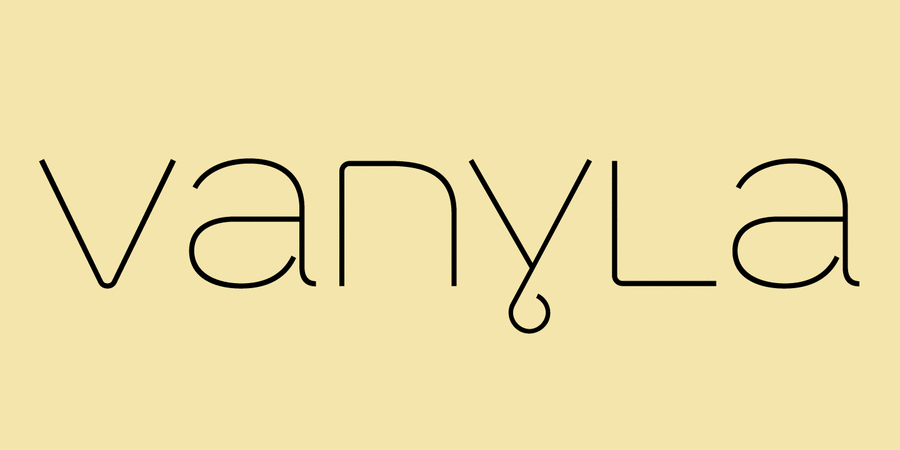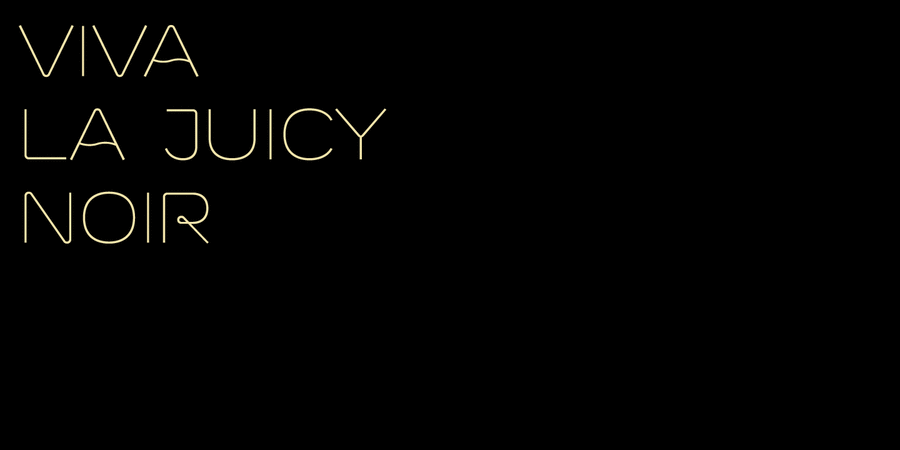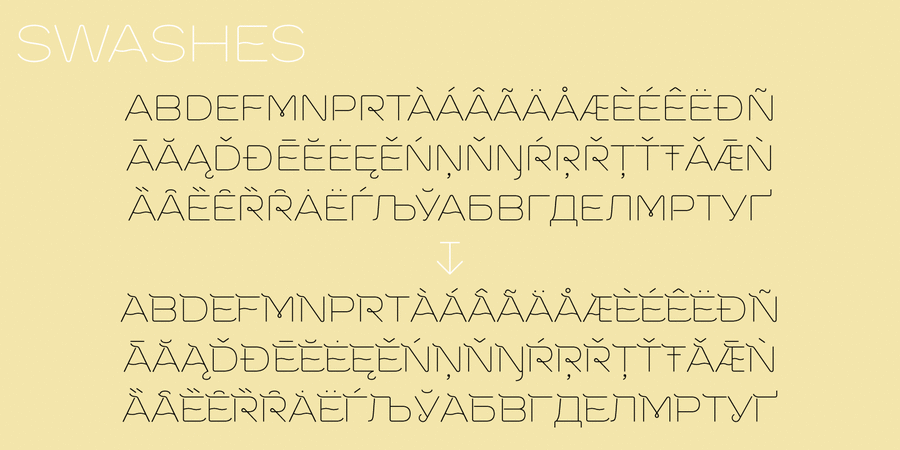
About Vanyla 4F UnicaseШрифт Vanyla 4F Unicase содержит 2 начертания и отлично подходит для рекламы, неоновых вывесок, журнальных заголовков и другой акциденции. Разработан Сергеем Ткаченко в 2013 году.
Associations for font family Vanyla 4F UnicaseTypeface personality and character:
neon, party, delicate, smooth, clean, easy, chilly, fresh, fashionable, urban, thin, modern, laconic, freewheeling, weightless, transparent, intimate, clubbing, flexible, distinctive, original, unusual, expressive, youth, positive, artistic, musical, popular, Soft, curved, tender, air, wire, pretty, nice, night, girlish, agile, dynamic, creative
city, perfumery, lotion, beauty, Eau de Toilette, shampoo, cosmetics, fashion, diet, design, hygiene, purity, recreation, sea, holiday, cafe, bar, alcohol, night club, entertainment, attraction, TV, cinema, decoration, beach, interior, accessories, show, musical, music, stage, barbershop, dress, clothes, party, partying, ASMR, cocktail, dance, disco, aquadiskotheque, yoga Typeface associated with age: